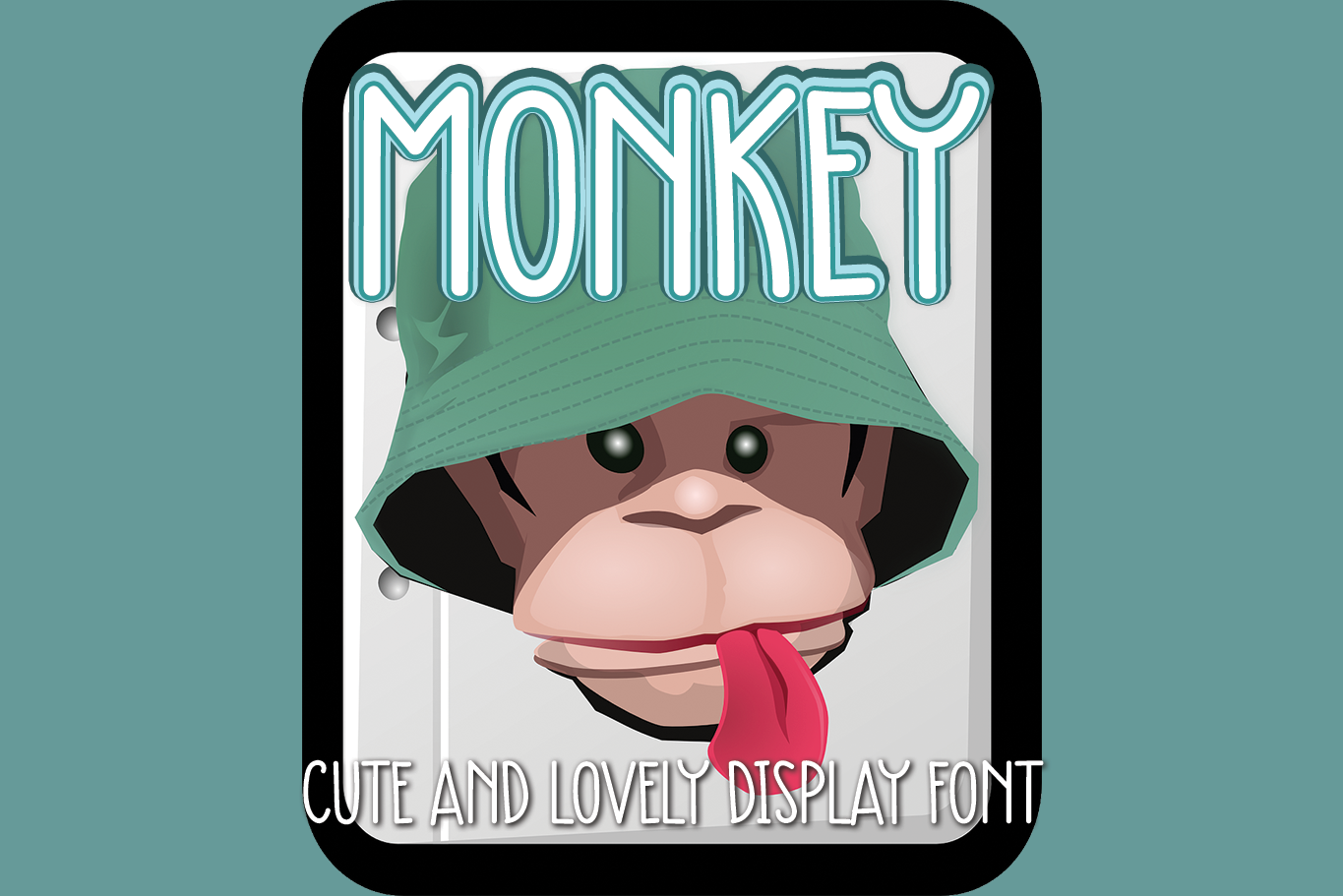
Monkey Font – Download Grátis
A fonte ‘Monkey Font’ é perfeita para aqueles que buscam uma mistura de simplicidade com personalidade. Seja ela usada em slogans de quadro branco ou materiais didáticos, esta tipografia escrita a mão oferece um toque autêntico e atemporal aos seus projetos gráficos. Com sua aparência realista e carregada de emoção, ‘Monkey Font’ adicionará um aspecto pessoal e verdadeiro às suas criações digitais. Seja você designer de grafismo ou criador de conteúdo online, esta fonte certamente irá adicionar um toque único ao seu próximo projeto. Não espere mais para experimentar a autenticidade e simplicidade desta fonte!